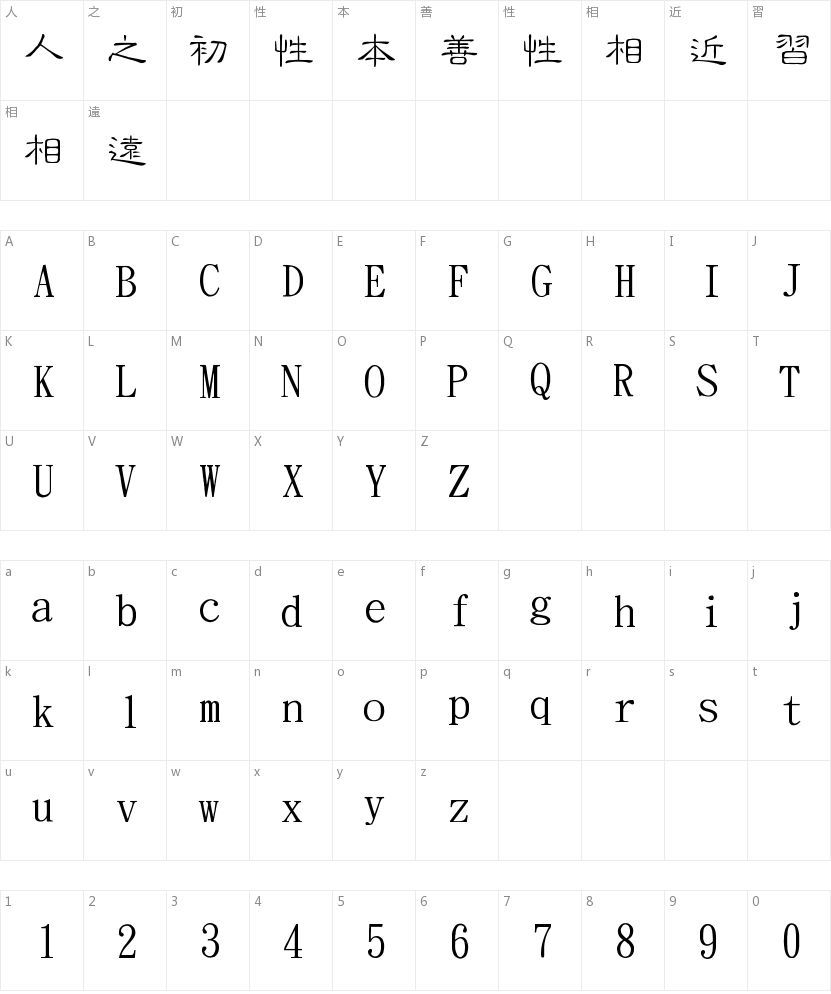
金梅新細隸國際碼是一種繁體中文字體,是由台灣漢字字體設計公司梅新科技有限公司開發的一款字體。金梅新細隸國際碼字體以台灣繁體中文的拼音碼為基礎,結合現代漢字輸入法的技術,提供了一種更加細膩、更加精美的繁體中文字體。金梅新細隸國際碼字體的特點是字形清晰、細膩、精美,字體寬度適中,字符細節豐富,兼容性強,可以在多種操作系統和應用程序中使用。內容介紹
金梅新細隸國際碼是一款非常不錯的手寫藝術字體,具有很好的視覺感,適合於文化類的宣傳設計、商業類品牌的廣告和產品包裝設計以及個性化文字排版等較多場景。